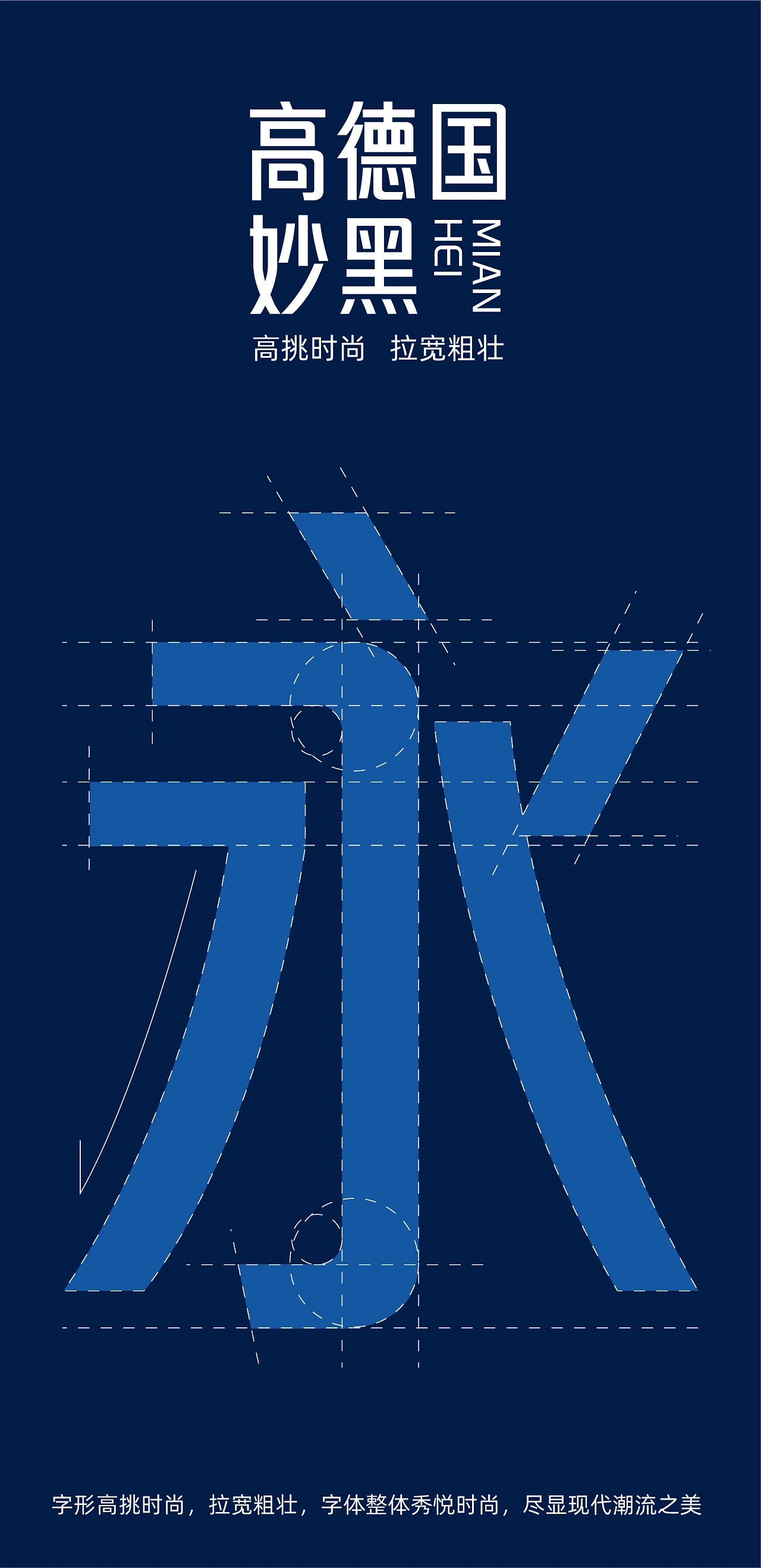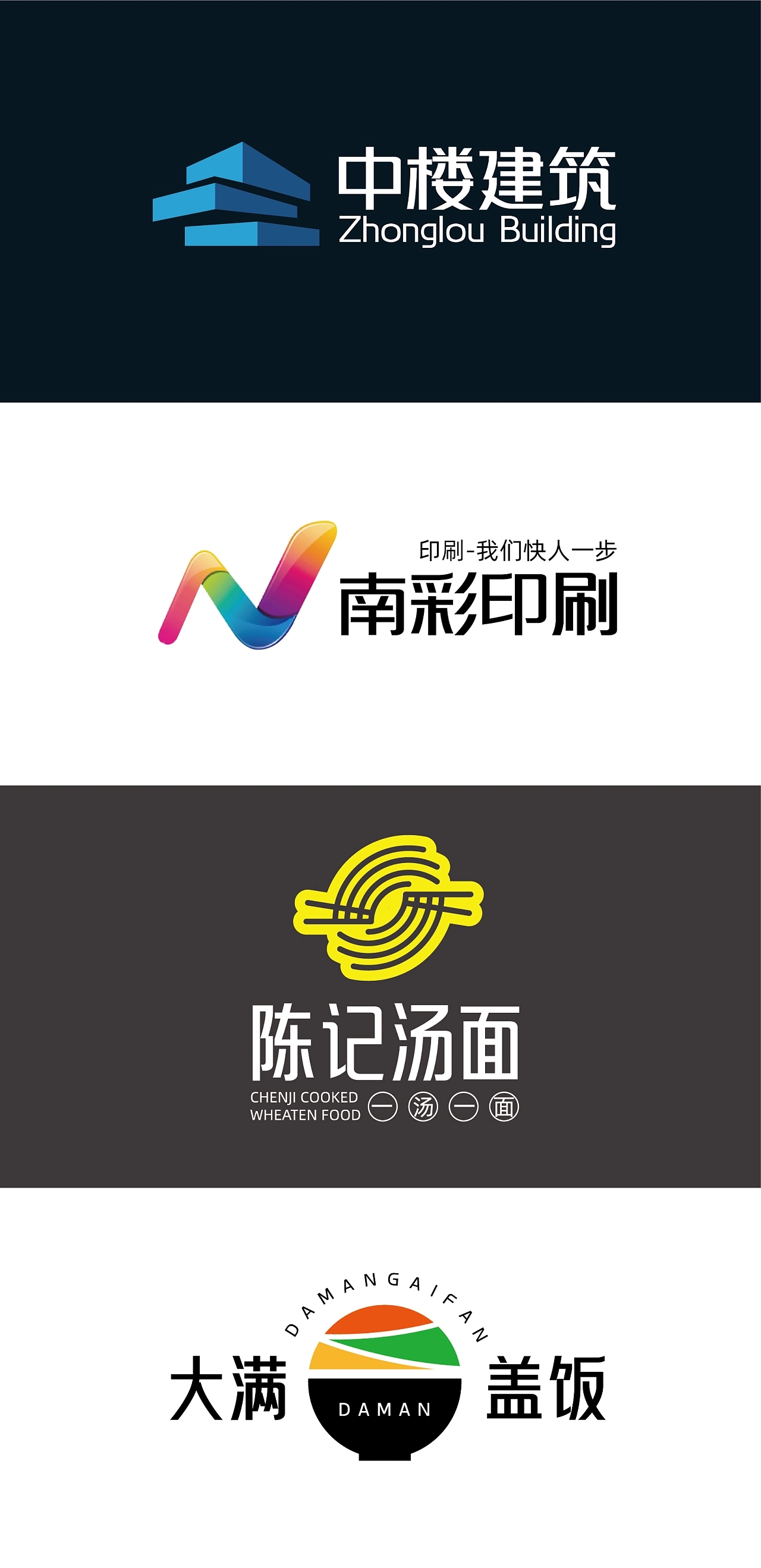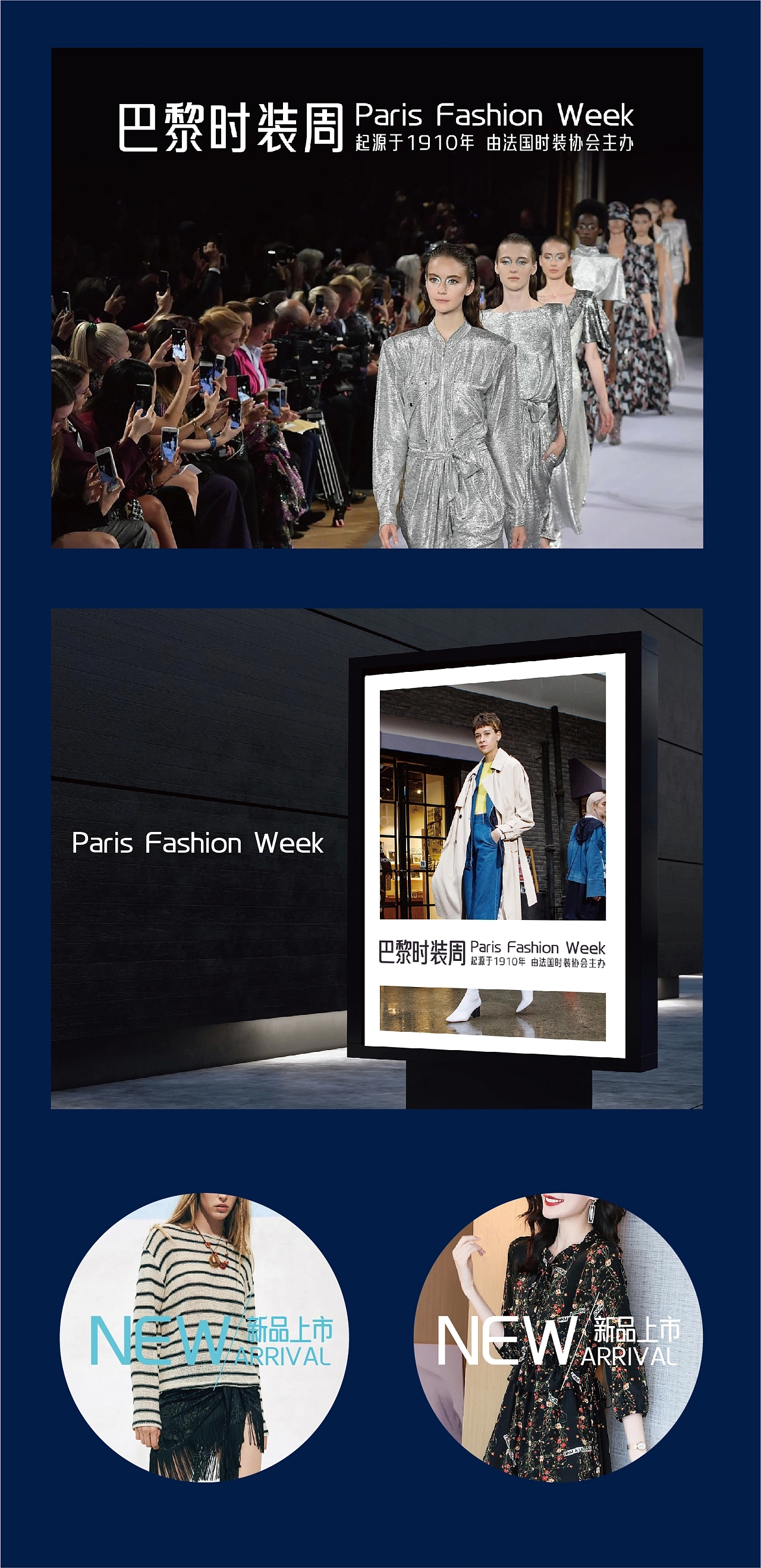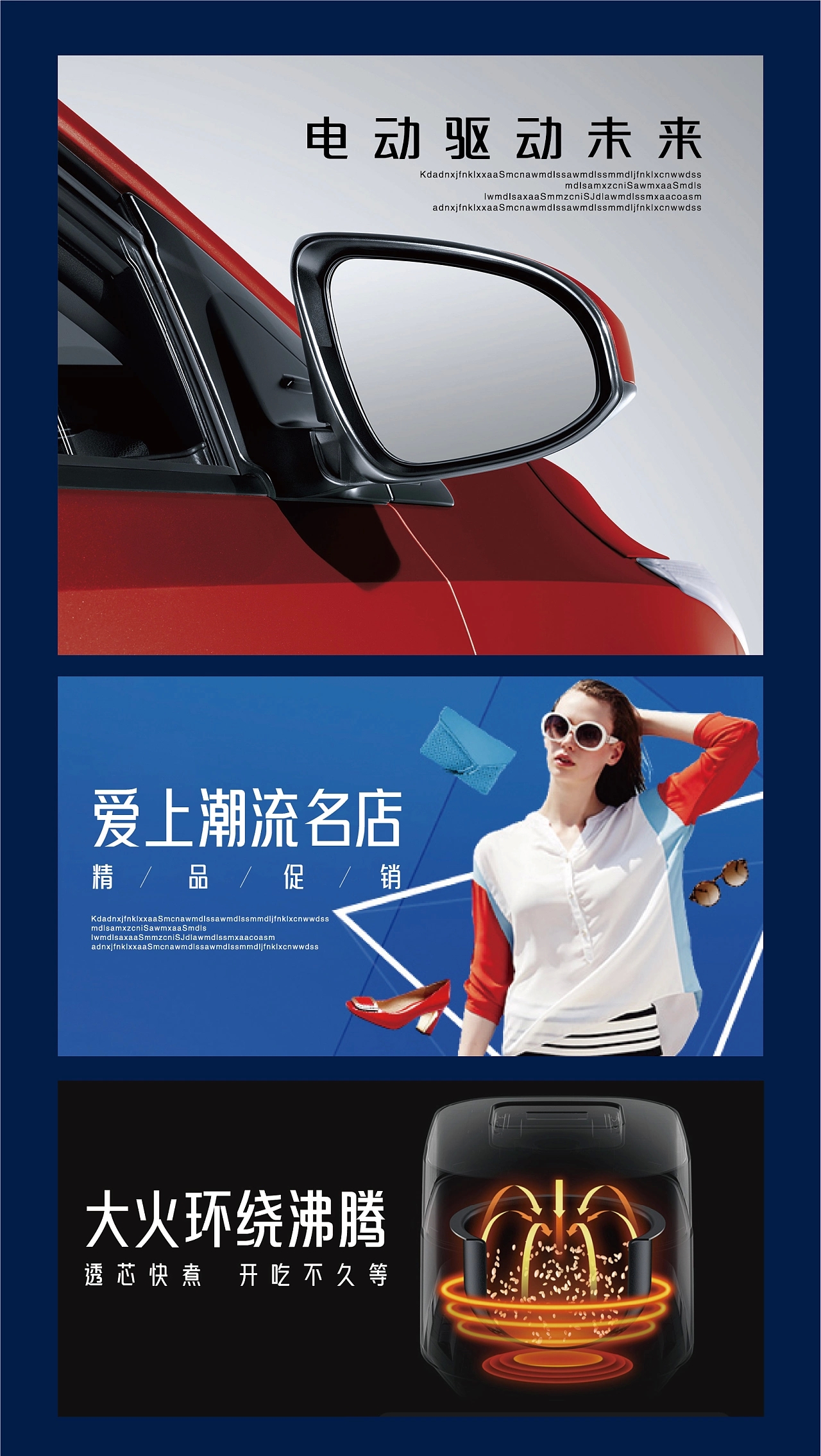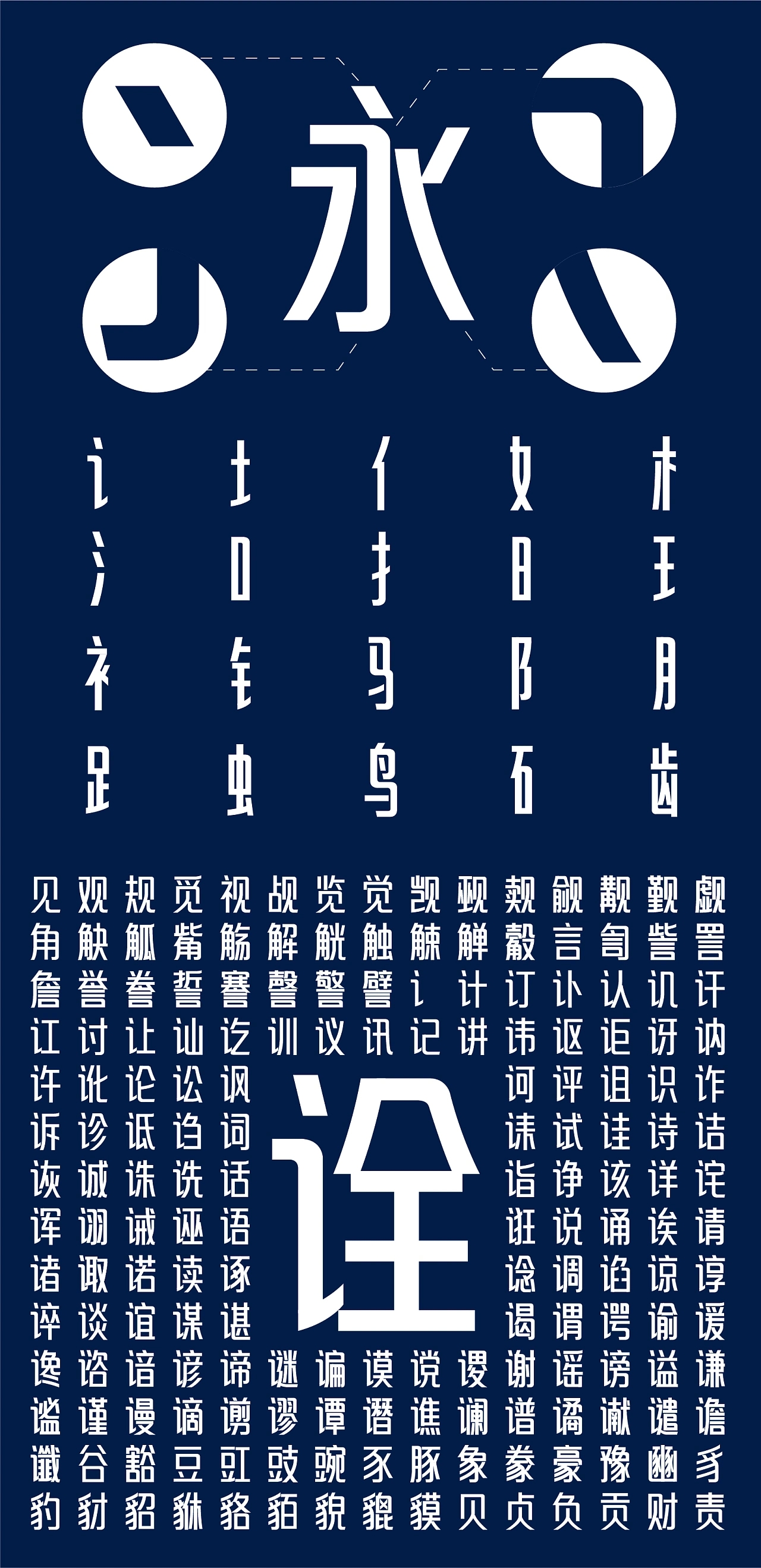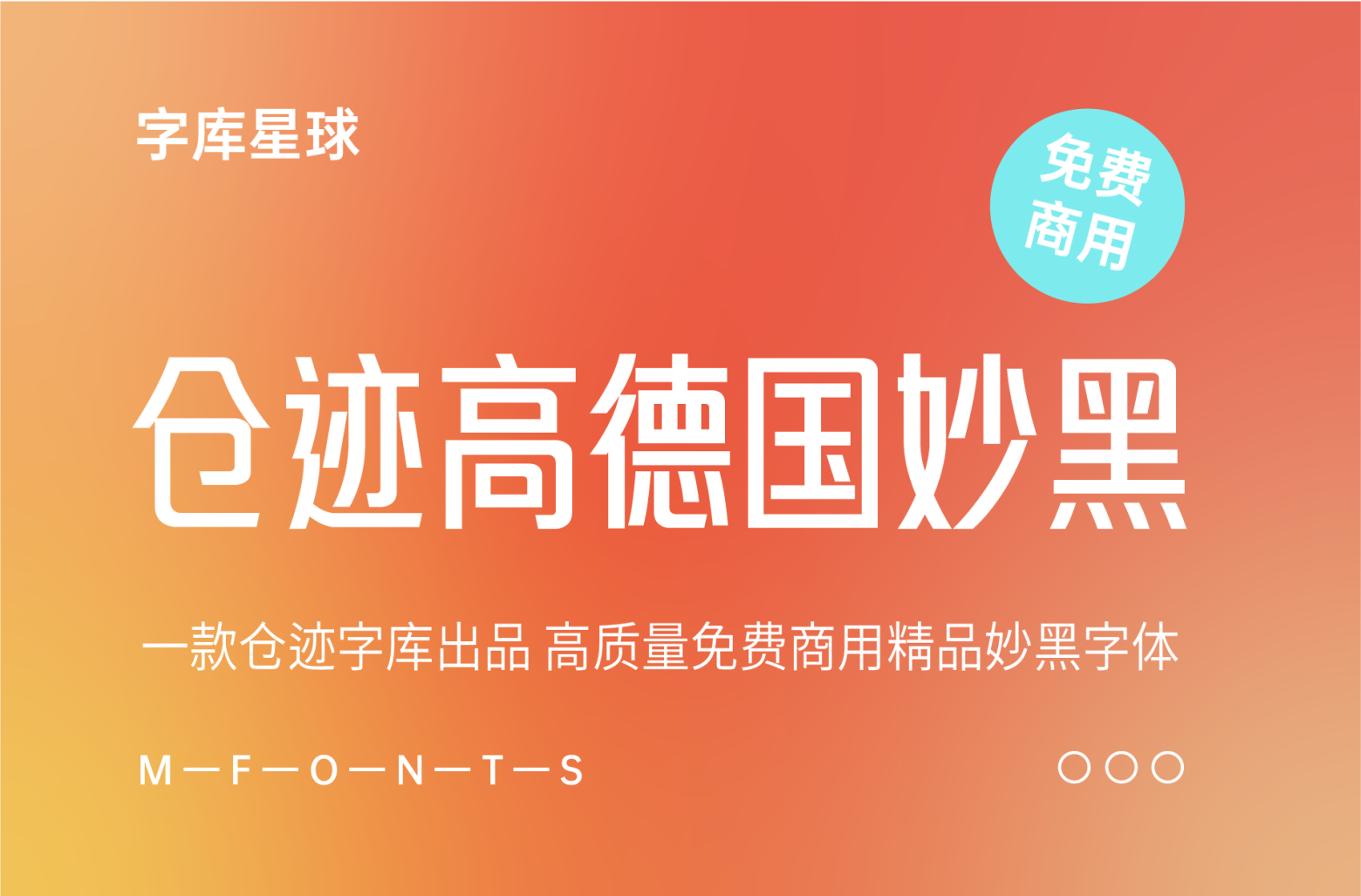
仓迹高德国妙黑
仓迹高德国妙黑是南京的高德国设计(仓迹字库)推出的一款免费商用字体,首发于站酷。据作者高德国称,这是一款收藏几年前的参赛样稿,从动笔到完工,陆续也有一年有余,总算能和大家见面了。当初这款字体有和字体厂商谈过,不过价格太低,作者放弃合作,打算自己开发这款时尚感十足的字体,开发的时候其实几经修改,因为黑体款式比较多,稍微不注意就有撞车危险,感觉修改就是避坑,不管如何今天和大家见面了。
高德国妙黑体高挑时尚,拉宽粗壮,做品牌设计必备,做广告标题良药,独特的高挑结构,使字体在商业创意设计中,可以更好的将字形与创意互相结合应用,能更好的为设计师服务,字体在各种行业众多场景都有出彩表现。